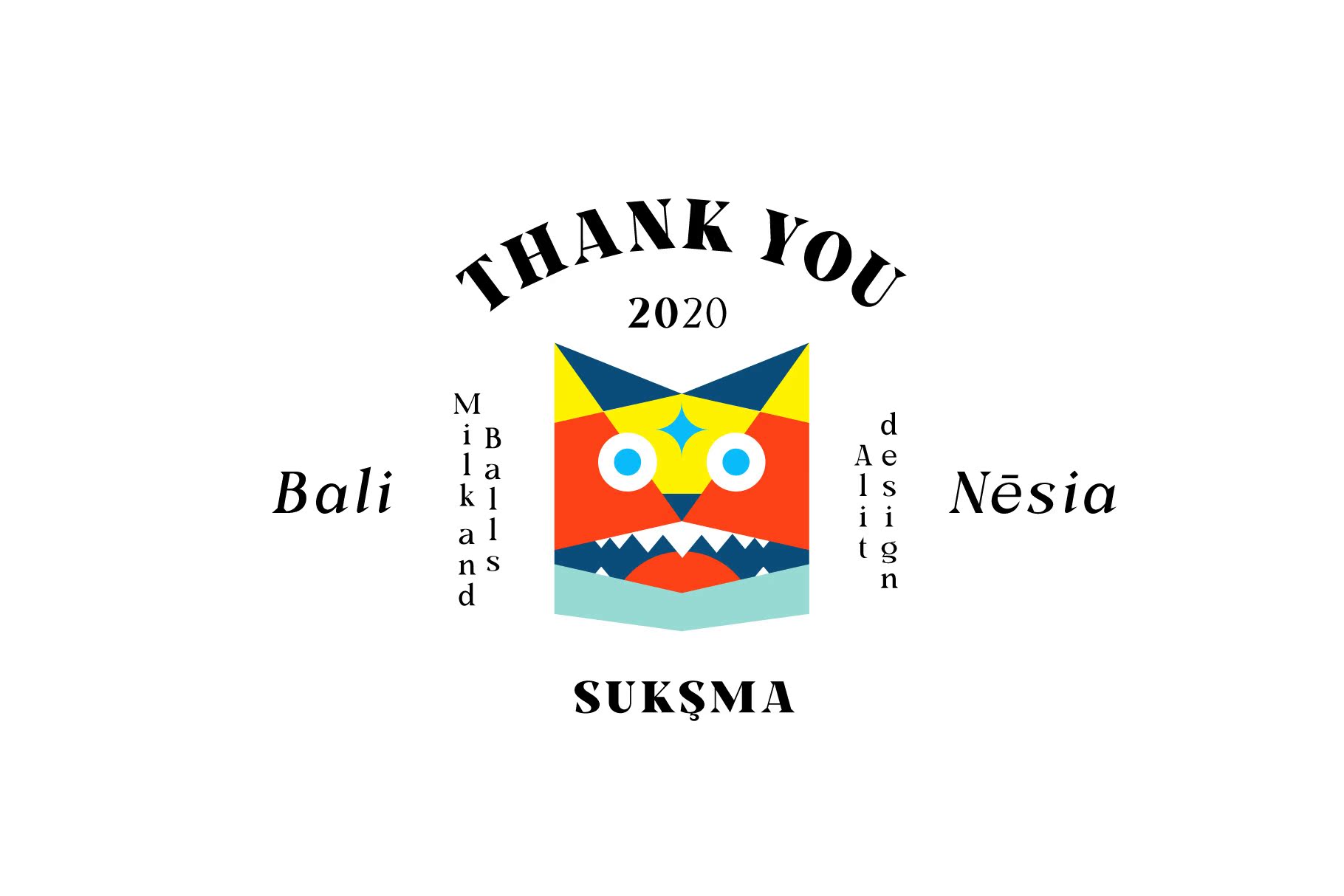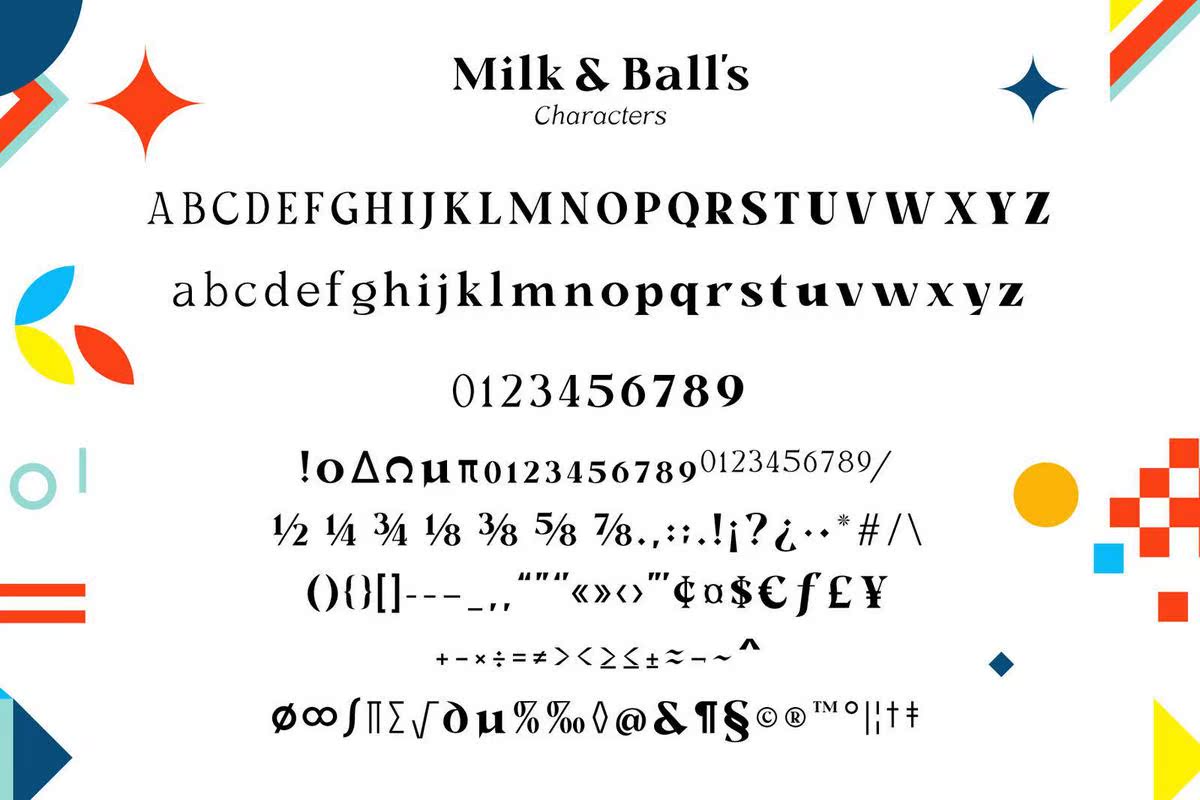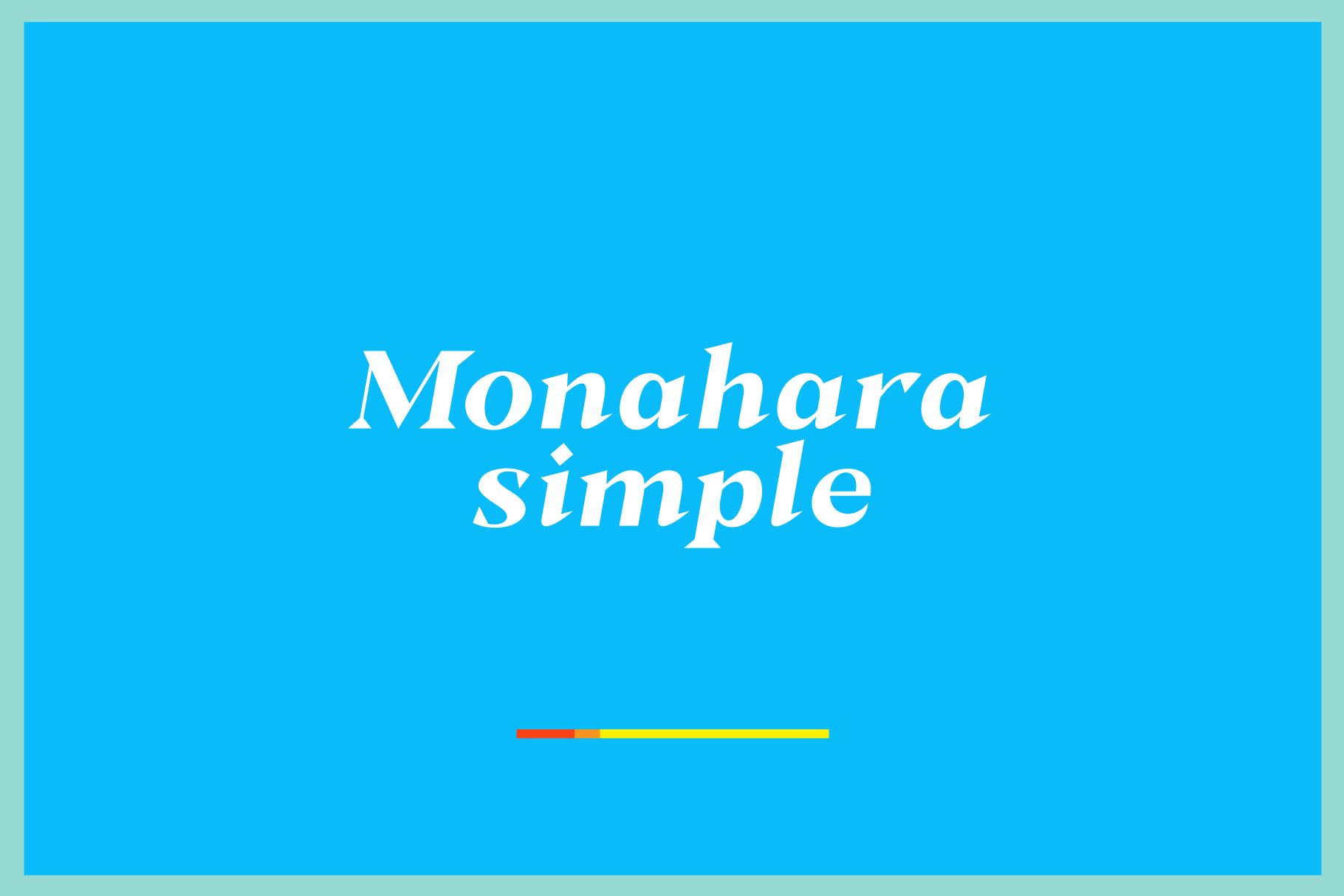
介绍了米尔坎贝尔家族。这一特征对于大胆和形式化的设计概念来说似乎是严格和决定性的。其独特的形状使得设计与其他家族有所不同。米尔坎贝尔家族非常适合头文本、体文本和段落的第二个主题,因为除此之外,还有11个家族包含从重到重的内容,还有一个统一版本。SoMilkandBall的所有内容都是完整的,并且适合于任何时候都可以使用的内容的集合。不要使用多语言,因为MilkandBall是由多语言支持的。介绍了MilkandBall的完整家族。这个特征对于粗体和形式化的设计概念来说似乎是严格和决定性的。它的独特形状使得设计与其他设计有所不同。MilkandBall适合于头文本、体文本、,第二段的内容是因为共有11个家庭成员来自于一个较重的家庭,此外,家庭成员也是一个统一的家庭成员。因此,MilkandBall的所有内容都是完整的,并且适合于任何时候都可以使用的内容。不要使用两种语言,因为MilkandBall的支持是多语言的。